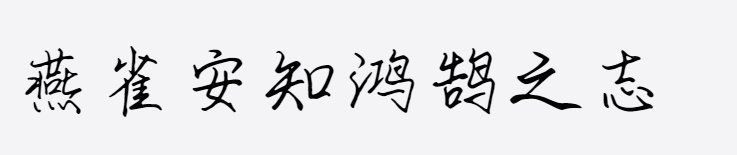
新字上线「上首鸿志手写体」一款潇洒有力量的手写字体
字体名称:上首鸿志手写体
字体类别:手写字体
名字灵感来源于陈胜的“燕雀安知鸿鹄之志”这句豪言壮语,并且字体手写者姓名里也有一个“志”字,两者结合,恰到好处。
上首鸿志手写体
字体如大雁(鸿)一样潇洒有力量,大气又端庄,给人惬意舒适的感觉,也希望能传达一种正能量。适用于书信文案、广告标语、商业广告等场景。
上首鸿志手写体